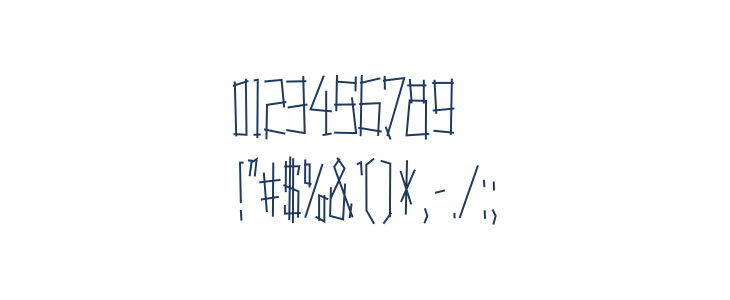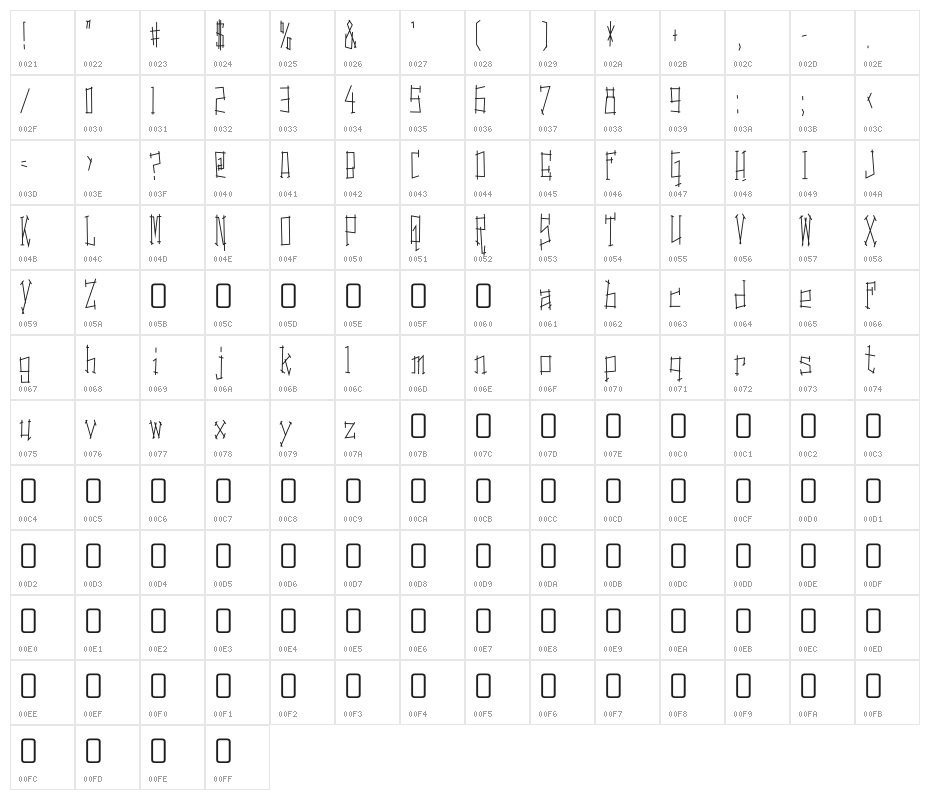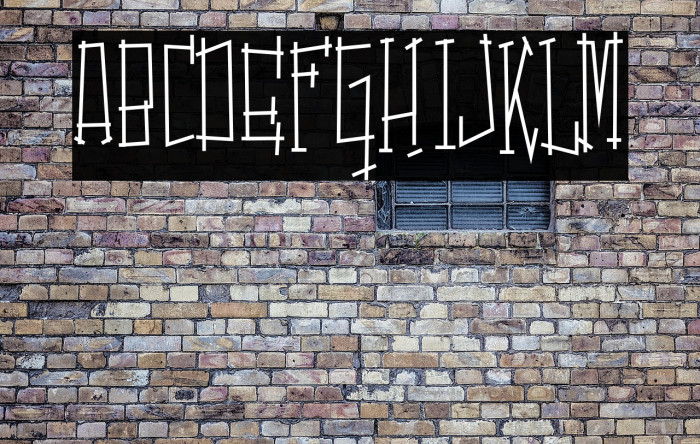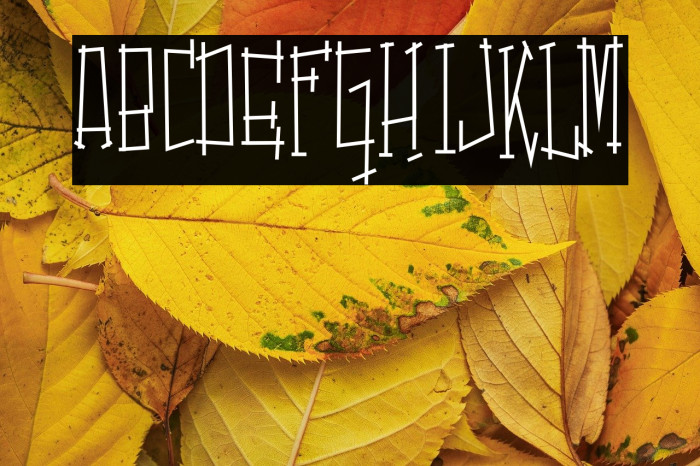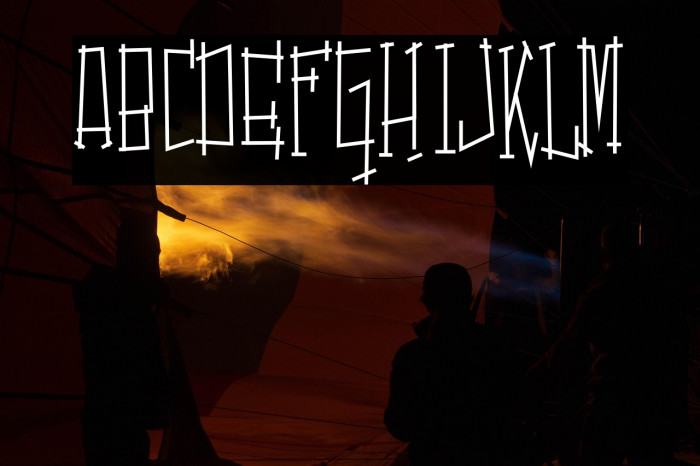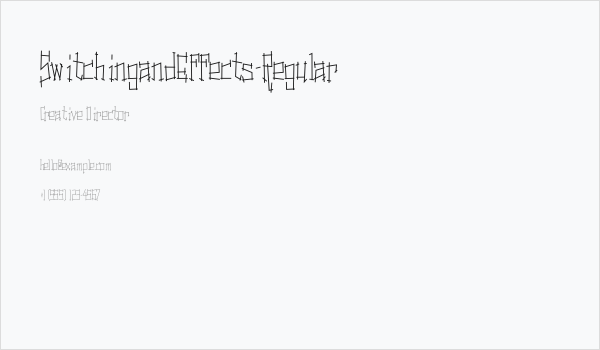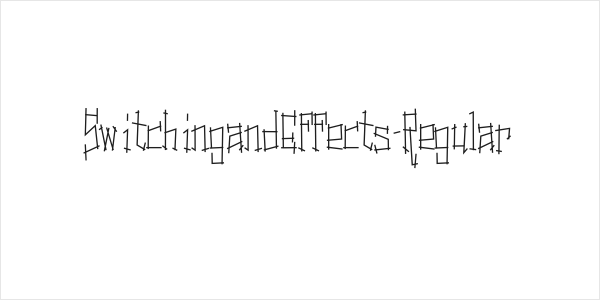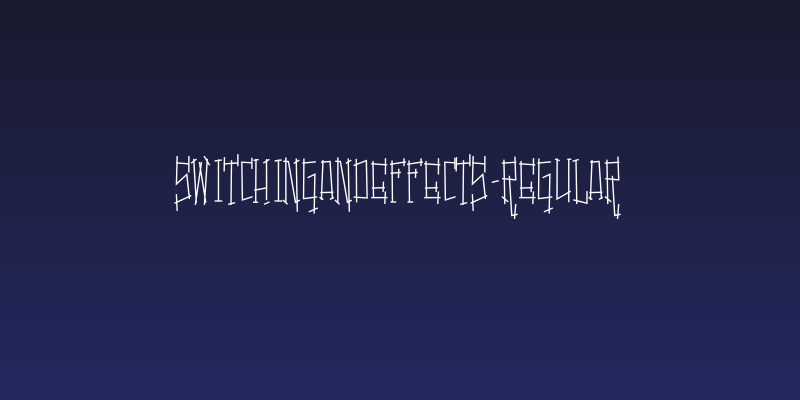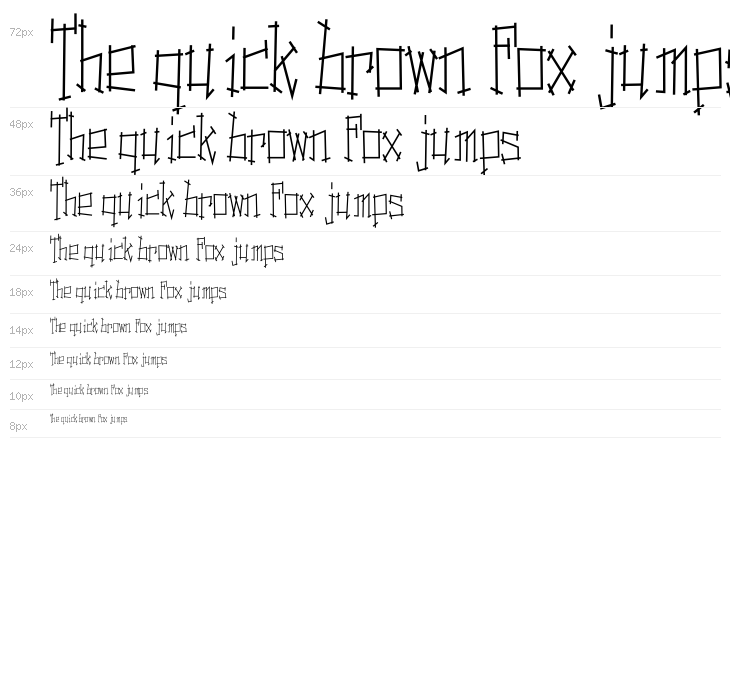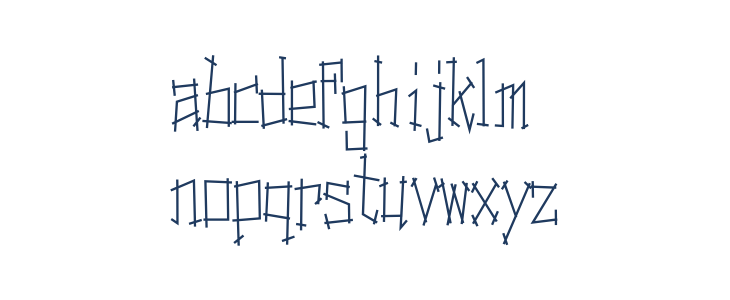
SwitchingandEffects-Regular Font
✎ Futuristic
| Kategorien | Futuristic |
| Gesamtstil | Futuristic, Edgy |
| Anwendungsfall | Logos, Headlines, Posters |
| Vorgeschlagene Projekte | Ideal for sci-fi themed designs, tech-related branding, video game interfaces, and edgy poster art. |